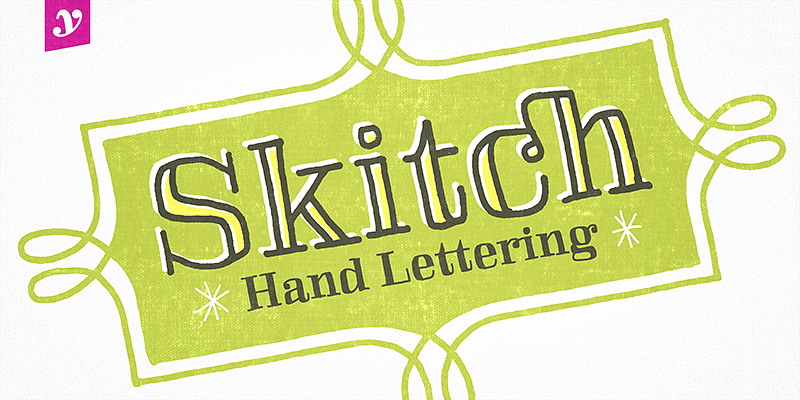
Los tipos de letra de Yellow Design Studio se pueden describir en cuatro palabras: de calidad superior, versátiles, innovadores y distintivos. Ryan Martinson ha diseñado una gama de familias de gran popularidad y de excelente factura que aparecen en campañas a gran escala en diferentes medios de comunicación. Incluso los diseñadores han votado estas tipografías como las fuentes más populares, lo que demuestra un talento especial para crear familias modernas, vistosas e increíblemente útiles. Yellow Design Studio tiene los tipos de letra que te ayudarán en tu próximo proyecto de gran repercusión.